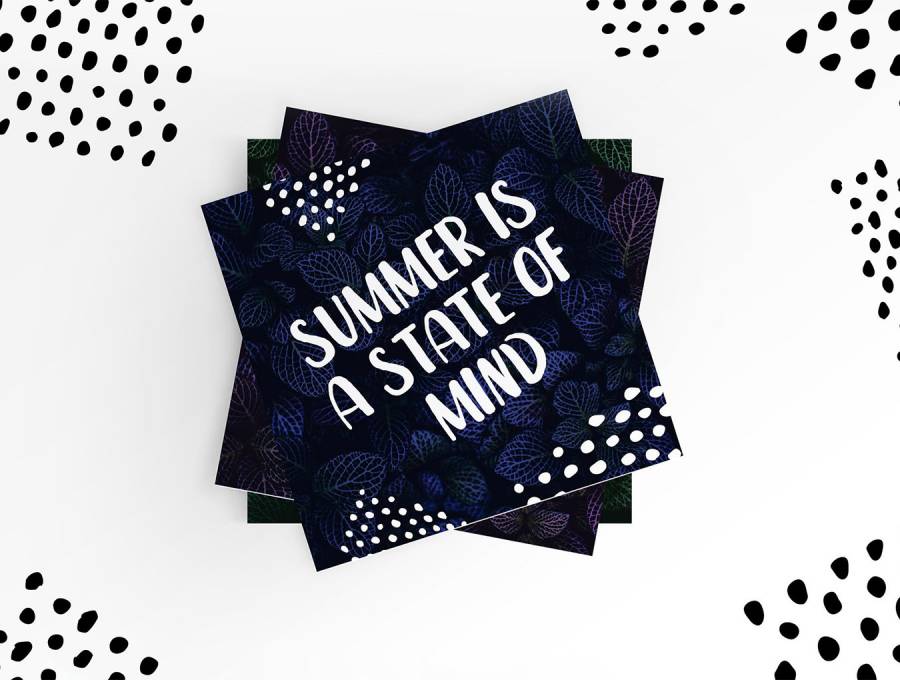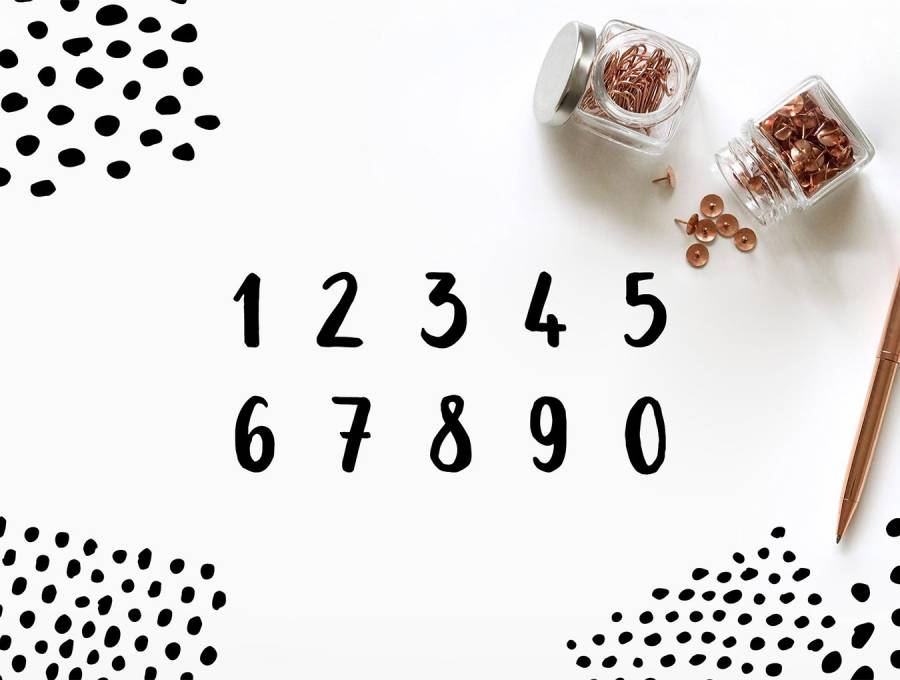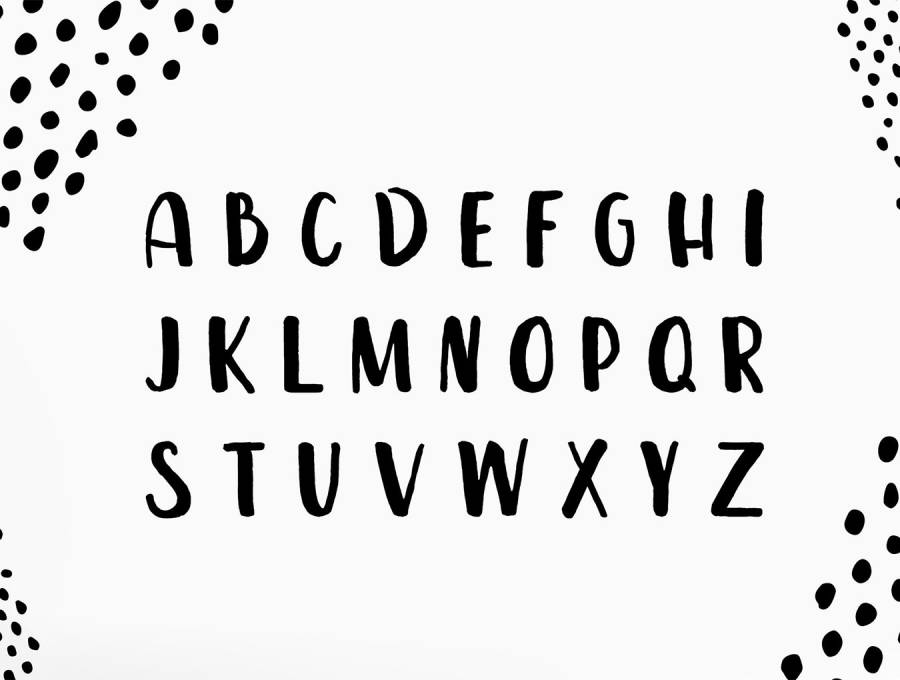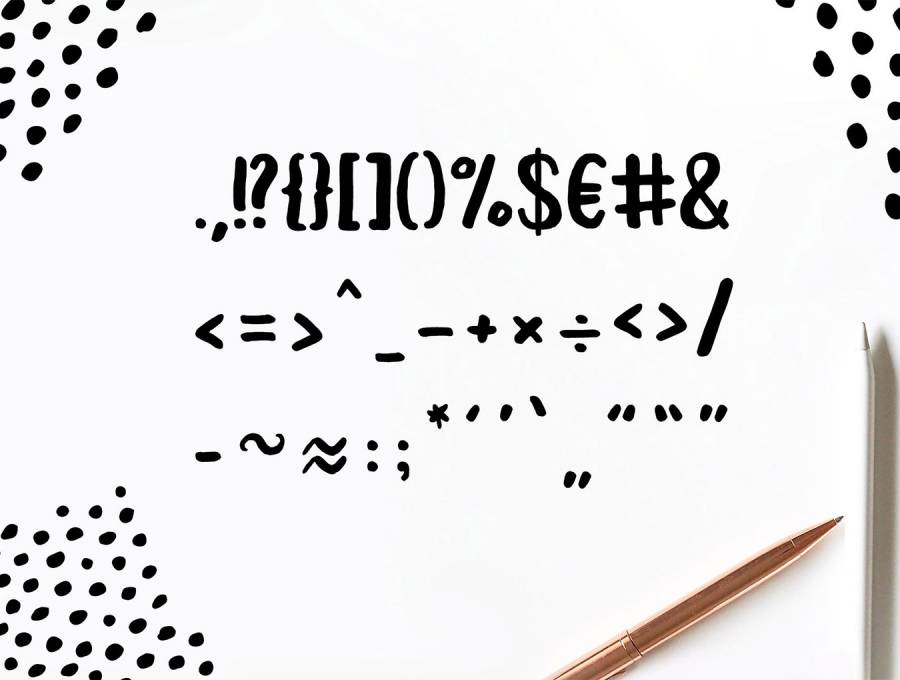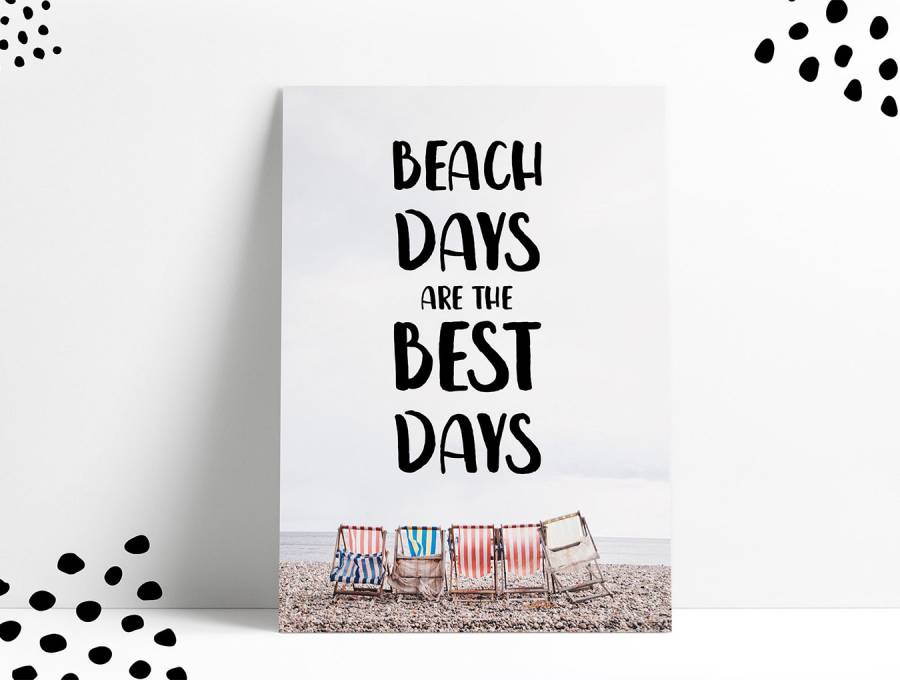
手绘字体大写画笔英文字体下载
Hand Drawn Font Uppercase Brush Font., Leira Brush Font
Leira手绘字体是手绘笔刷大写字体。这种字体具有手写的感觉,因此它将为您的设计提供个性化的触感。大胆的角色将脱颖而出,易于阅读。它非常适合创建身份,徽标,海报,卡片和包装设计。包括大写字母,数字,符号。